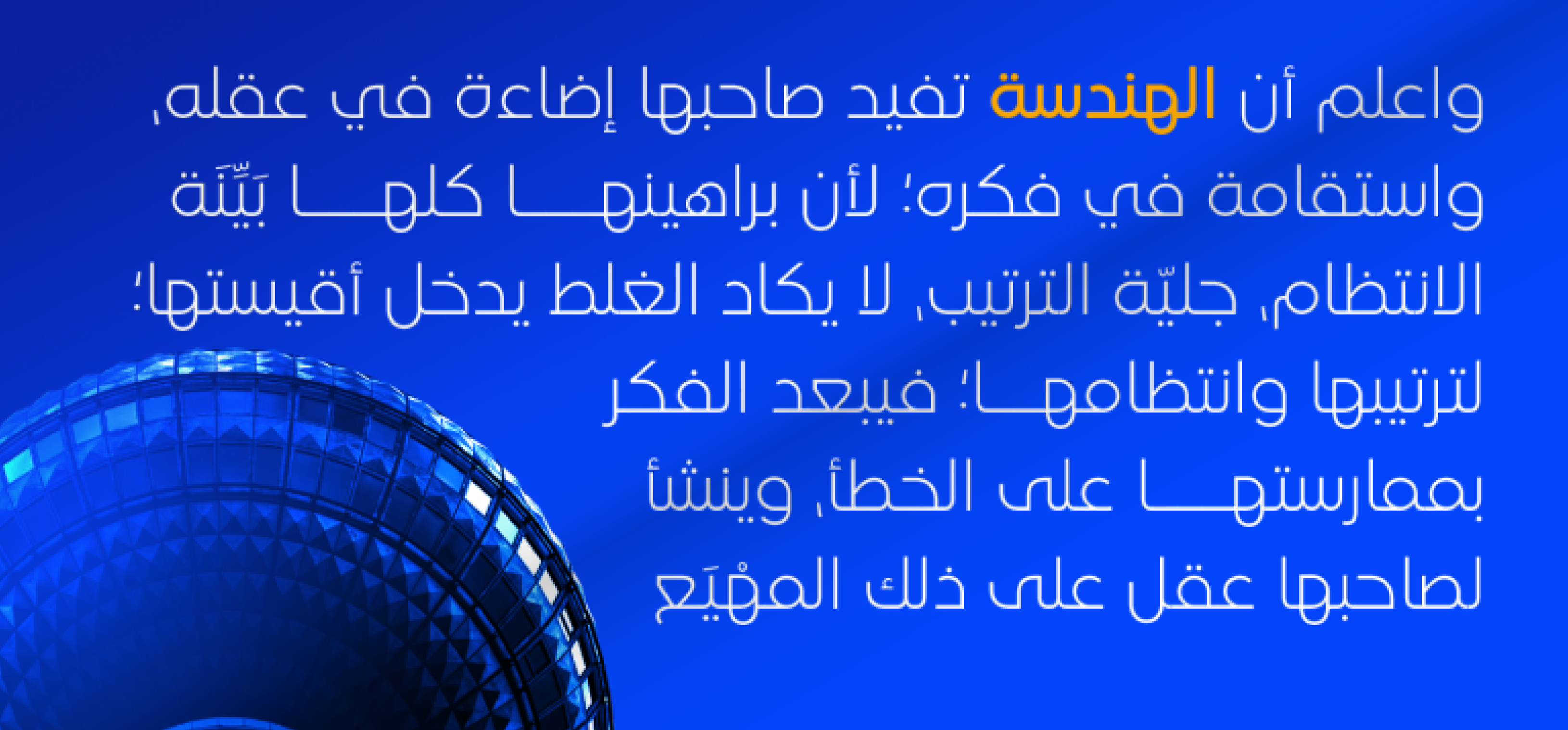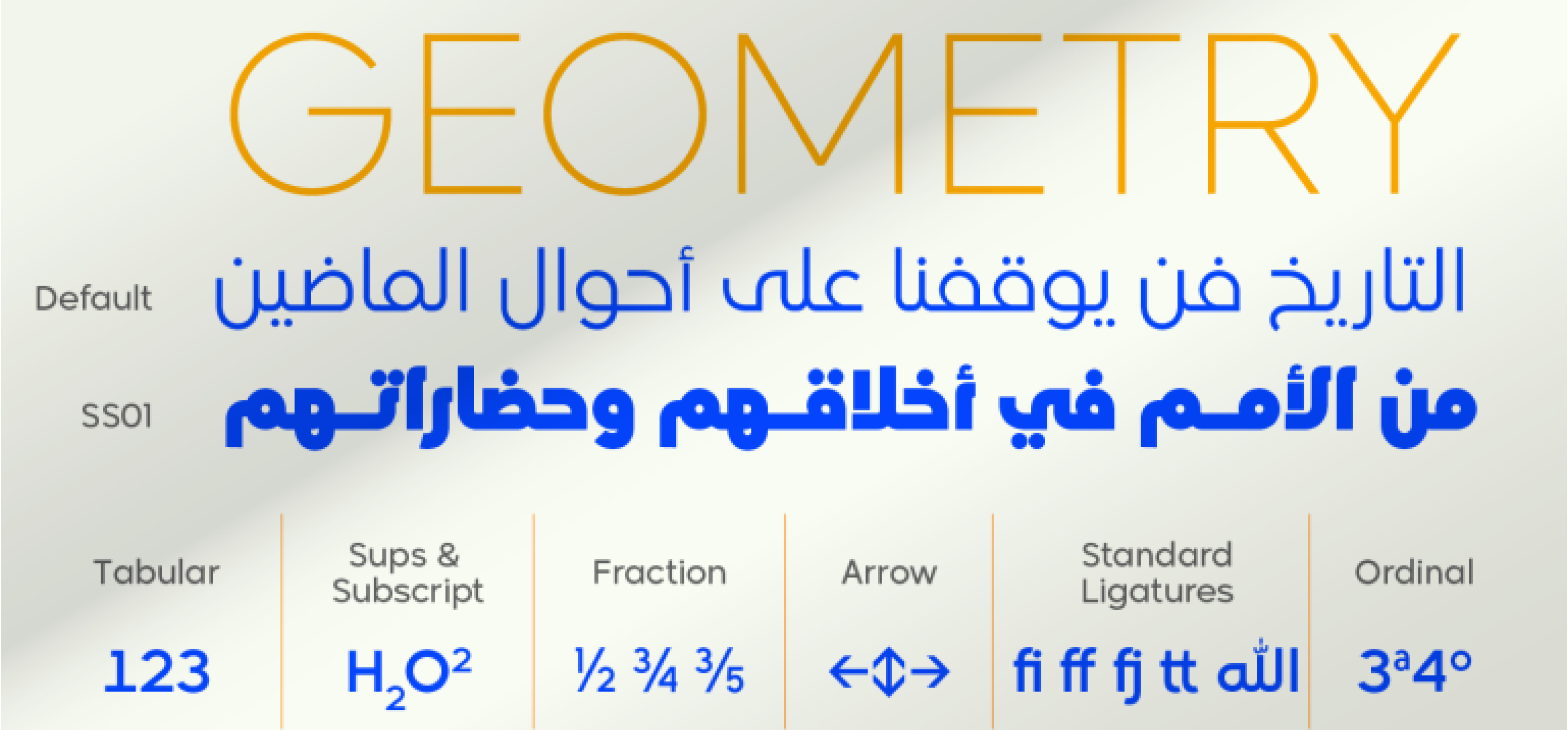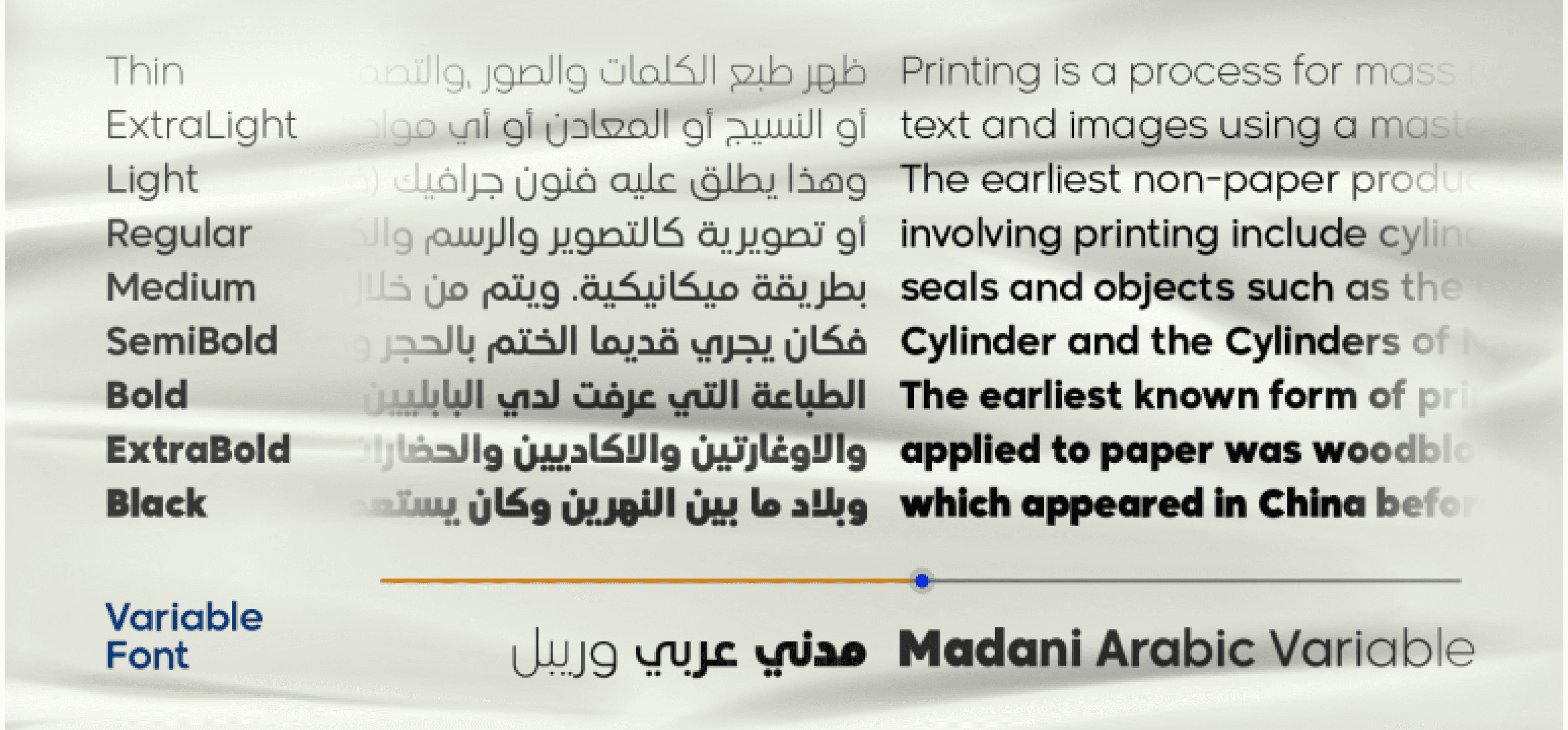
خط Madani Arabic هو تجسيد حقيقي لفن الخط العربي، مستمد من عراقة وأصالة أسلوب الخط الكوفي.
يجمع هذا الخط بين أناقة الكوفي الكلاسيكي والطابع الهندسي العصري، ليُنتج مزيجًا متوازنًا ينسجم بانسيابية مع التيبوغرافيا اللاتينية.
هذا التناسق يجعله مناسبًا للاستخدام ضمن بيئات طباعية متنوعة ومتعددة اللغات.